Typografie macht Spaß – das zeigen die T-Shirts aus der neuen Kollektion von spatium, die mit einem Augenzwinkern altes Fachvokabular aus der Bleisatzzeit darstellen.
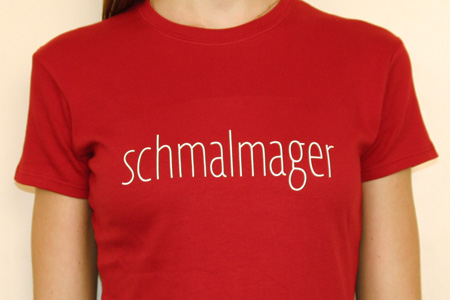
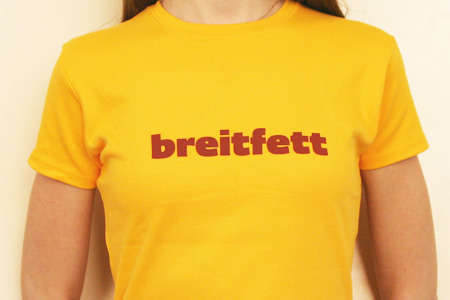
Kollektion Schriftgewicht
»Schmalmager« und »breitfett« sind als Begriffe viel anschaulicher als Thin condensed oder Black extended und auch in der entsprechenden Schrift gesetzt (Fedra Sans Display Hairline Compressed bzw. Black). Siebdruck auf Baumwollshirts.
Nomprel
»Nomprel« ist die Setzer-Aussprache des Wortes Nonpareille, das einen Schriftgrad von 6 Punkt bezeichnet. Das Motiv gibt es in zwei Varianten mit Schriften aus alten Musterbüchern, einmal gesetzt in der Block Signal und einmal in der Presto. Flockdruck in Sonnengelb oder Hellblau auf braunen Baumwollshirts.